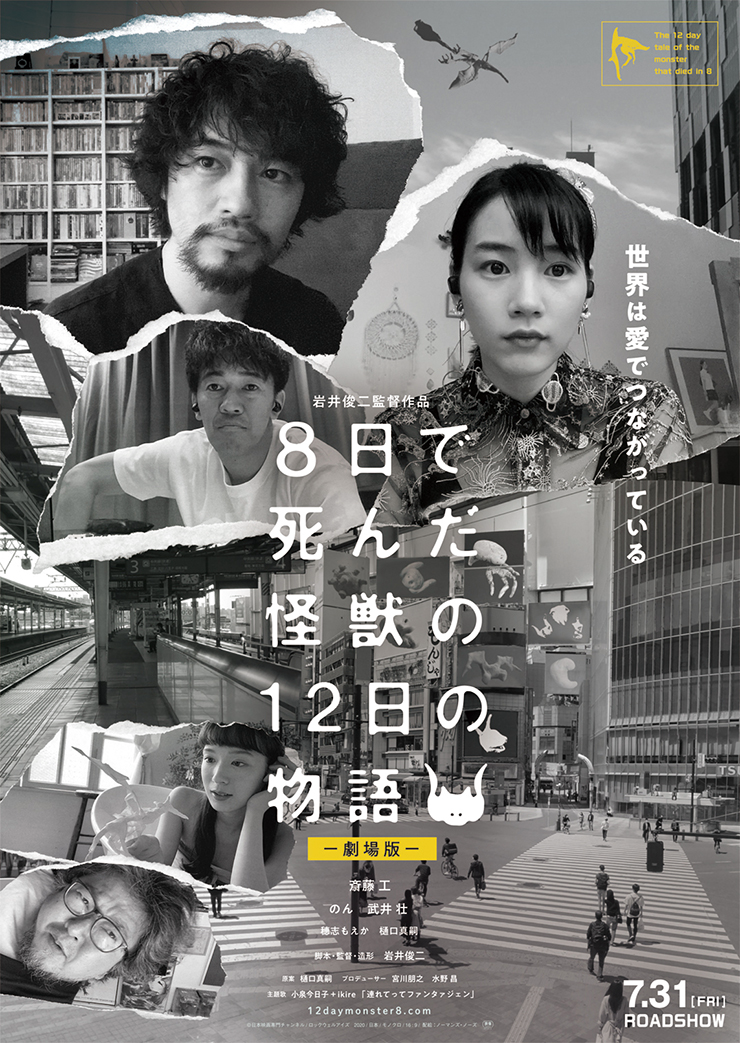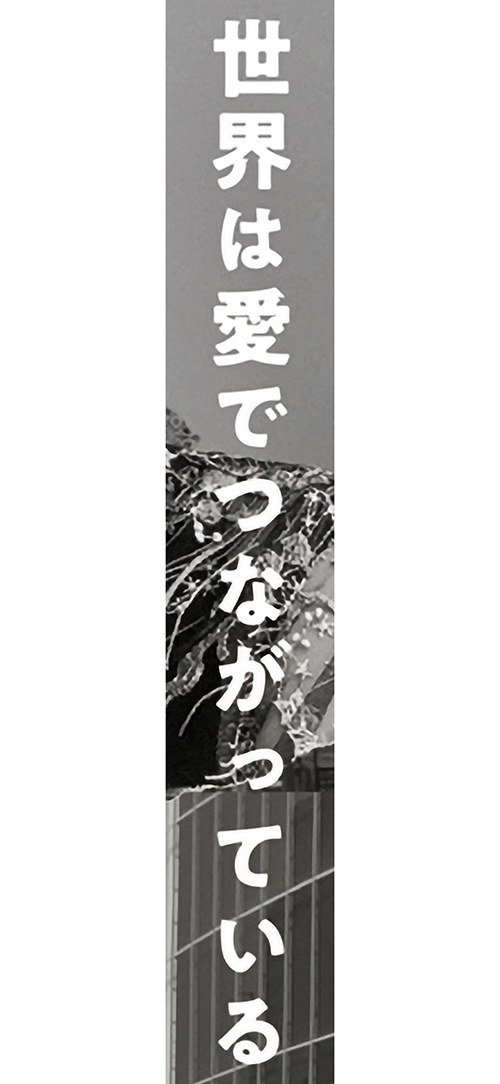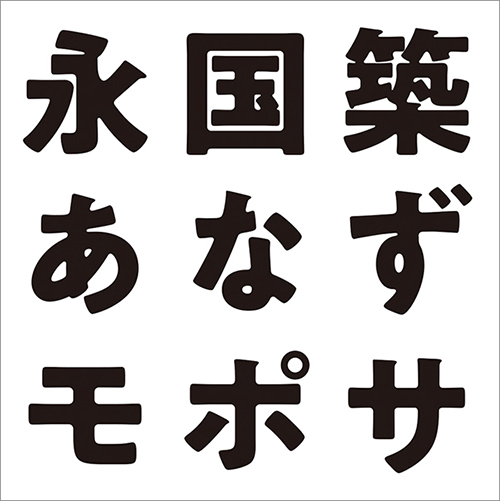
●Designer:石塚真央[Rockwell Eyes]
今回は映画『8日で死んだ怪獣の12日の物語 -劇場版-』のポスターの使用フォントを紹介。本記事はデザイン構成において重要な「フォント」の選定プロセスや加工方法を、貴重なプロの実例から紐解いてデザイン制作に役立てる連載です。
独特の風合いがあるゴシック体でリアルかつ幻想的に
ポスターでは、そのドキュメンタリーのようでありながらファンタジックでもある世界観や、メインモチーフである怪獣たちの存在感、「物理的に離れていてもつながりがある」という作品のテーマなどが、モノクロ写真のコラージュや破いた紙のテクスチャ、独特の風合いがあるタイトル文字などで表現されている。
Font.01「HGP創英角ゴシックUB」
輪郭のにじんだ文字でファンタジックに
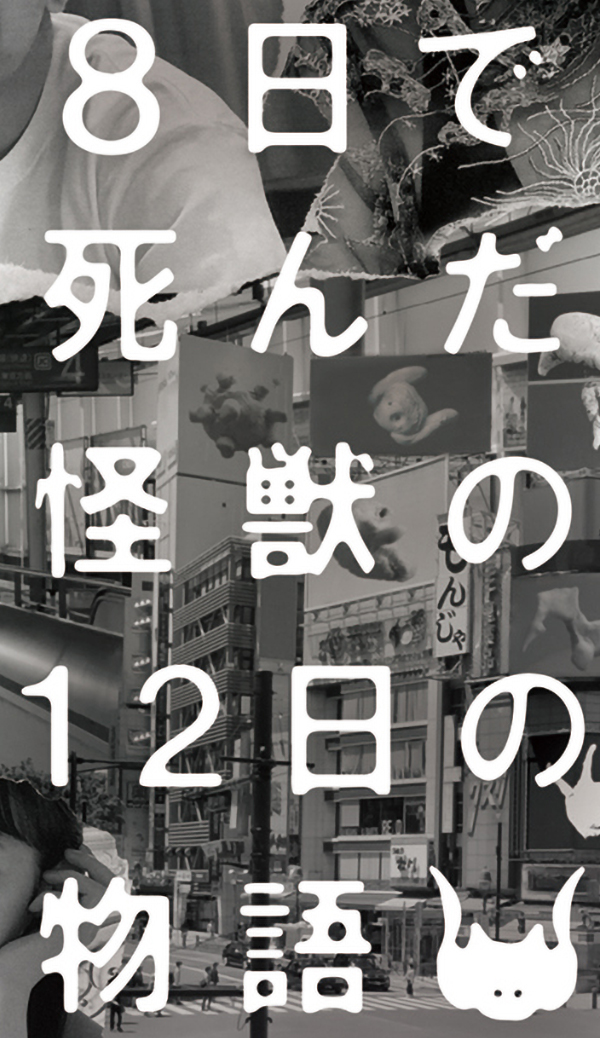
タイトルロゴは、YouTubeで配信される際に岩井俊二監督によって作成されたもの。オーソドックスな極太ゴシック体「HGP創英角ゴシックUB」(リコー)を少しぼかし、輪郭をにじませることで、リアルでもあり、どこかファンタジックでもある作品の世界観に合った独特の風合いが持たせられている。怪獣のマークは、そのタイトルロゴに合わせて劇場版用に新たに作成された。
Font.02「A1ゴシック M」
作品世界に合わせ親しみやすい書体に
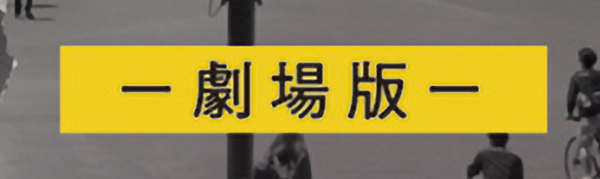
タイトルロゴの下に配置された「-劇場版-」の文字は、線画の交差部分に墨だまりのようなニュアンスのある「A1ゴシック M」(モリサワ)に。通常のゴシック体に比べて固くなりすぎず親しみやすい印象があり、作品の世界観にマッチしていたため選択された。
Font.03「A1ゴシック B」
他の文字要素と同様にアナログ的な書体を
キャッチコピーの文字は「-劇場版-」の文字と同じく、エレメント先端の角丸処理や線画の交差部分の墨だまりが特徴的なゴシック体「A1ゴシック」(モリサワ)に。作品のリアルかつファンタジックな世界観に合わせ、他の文字要素と同様にアナログ的な表情を持つ書体がチョイスされた。読み手に与える印象や可読性に配慮し、ウェイトは「B(ボールド)」が選択されている。
Font.04「A1ゴシック M」
他のフォントと書体をそろえて統一感を
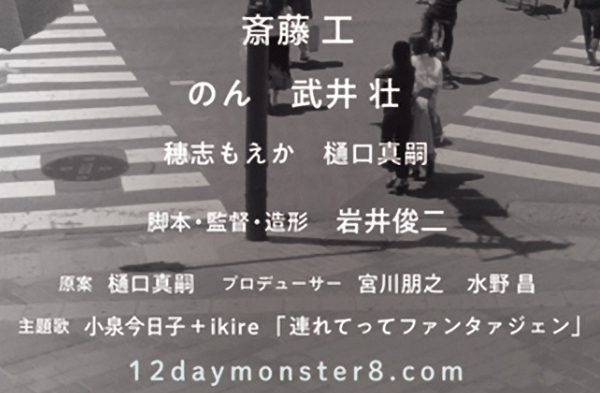
キャストやスタッフのクレジット部分は、「-劇場版-」の文字やキャッチコピーなどと同じ「A1ゴシック」(モリサワ)に。作品の世界観になじませ、ポスター全体に統一感を与えるため、他の文字要素と同じ親しみやすいゴシック体が選択されている。